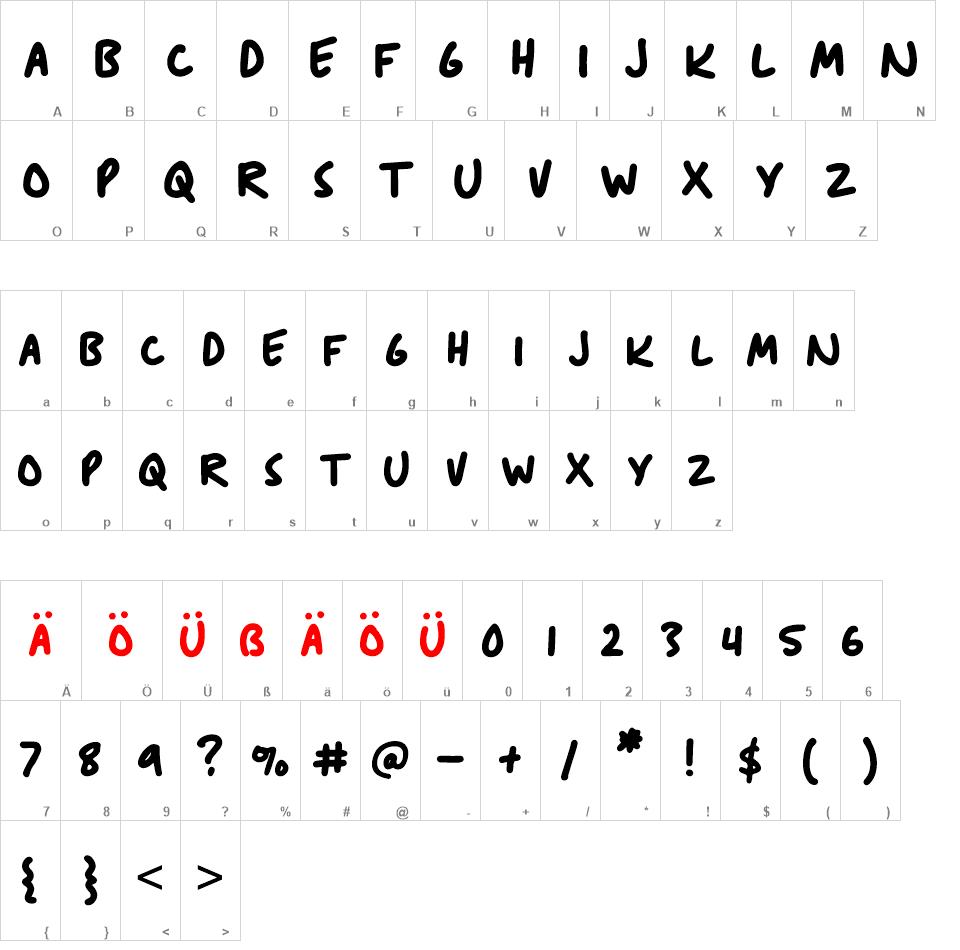
Anitype Journal
Anitype Journal ist eine animierte, handgeschriebene Schrift. Jedes Zeichen wird fünf Mal gezeichnet, um einen naiven Animationseffekt zu erzeugen, wenn es als Rahmen einer Animation verwendet wird. Es kann in CSS, Javascript oder sonstwie animiert werden, solange die Schriftarten wechseln!